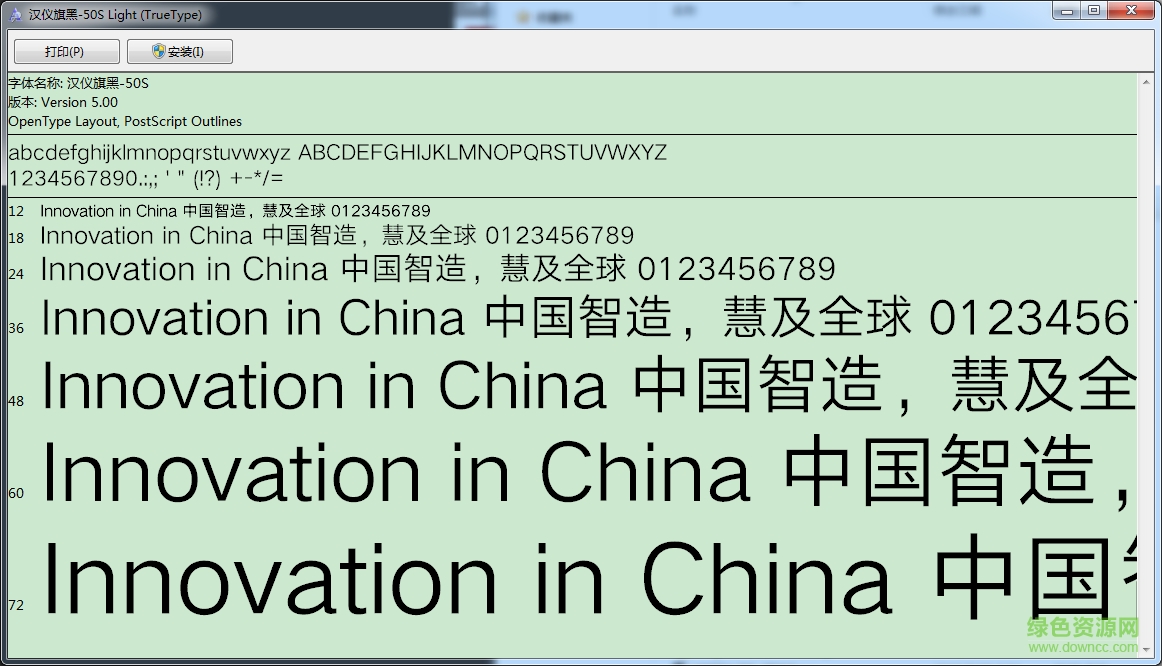
hyqihei ezs(漢儀旗黑50s)字體是一款挺拔美觀的漢儀字體,字體設(shè)計(jì)非常符合構(gòu)形標(biāo)準(zhǔn),線條流暢,比例適當(dāng),看上去落落大方,喜歡的小伙伴趕緊來綠色資源網(wǎng)下載吧!
結(jié)構(gòu)方正均衡,內(nèi)斂外收,筆畫平直,粗細(xì)一致,結(jié)體飽滿,連貫方正!